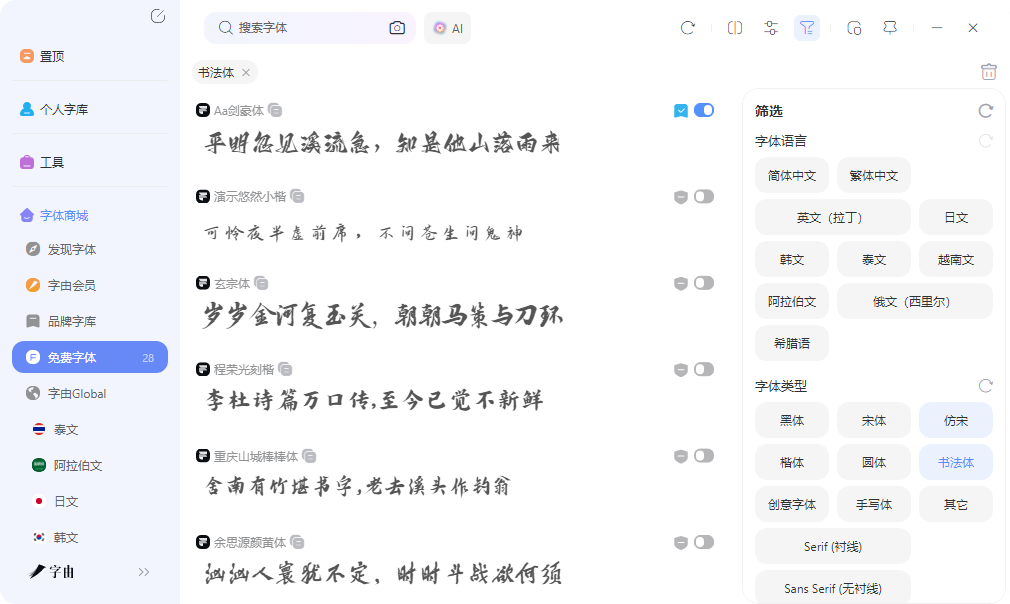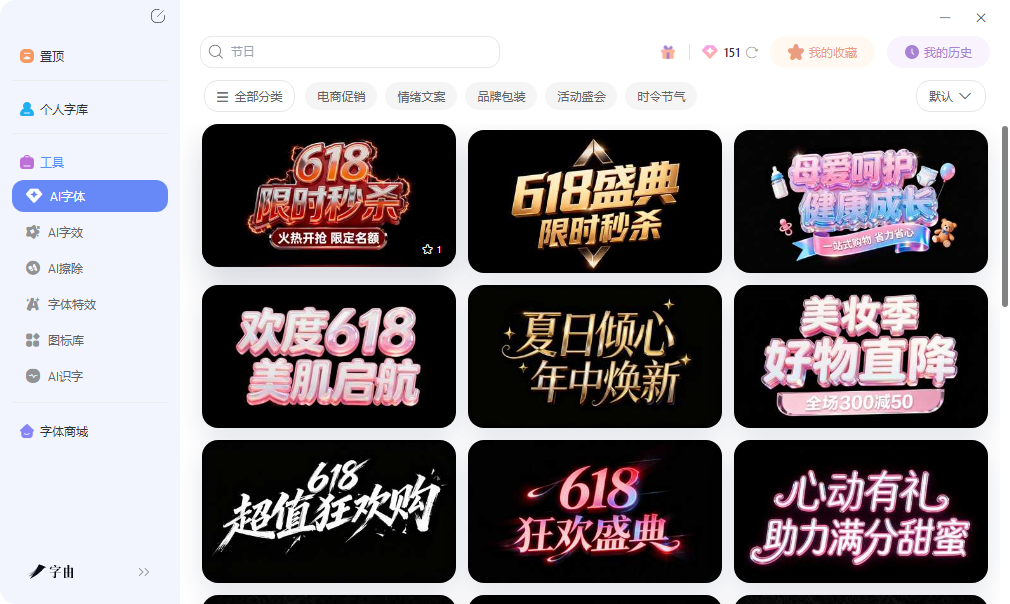
可以免费用的字体下载,中英文字体一站找齐
做设计最尴尬的事,不是创意卡壳,而是做到一半发现字体不能商用。很多人攒字体时只看效果不看授权,真到交稿时才发现某些字体仅限个人使用。与其事后补救,不如一开始就找可以免费用的字体渠道。这篇文章整理的五个平台,在商用授权方面都比较明确,中英文字体都有覆盖。
字由的字体库规模超过一万款,其中免费商用的超过三千款。这些字体来自优设、阿里妈妈、汉仪、蒙纳等正规厂商,授权链路清晰。每款字体的卡片上都标明了授权类型,免费商用、会员商用或单独授权一目了然。
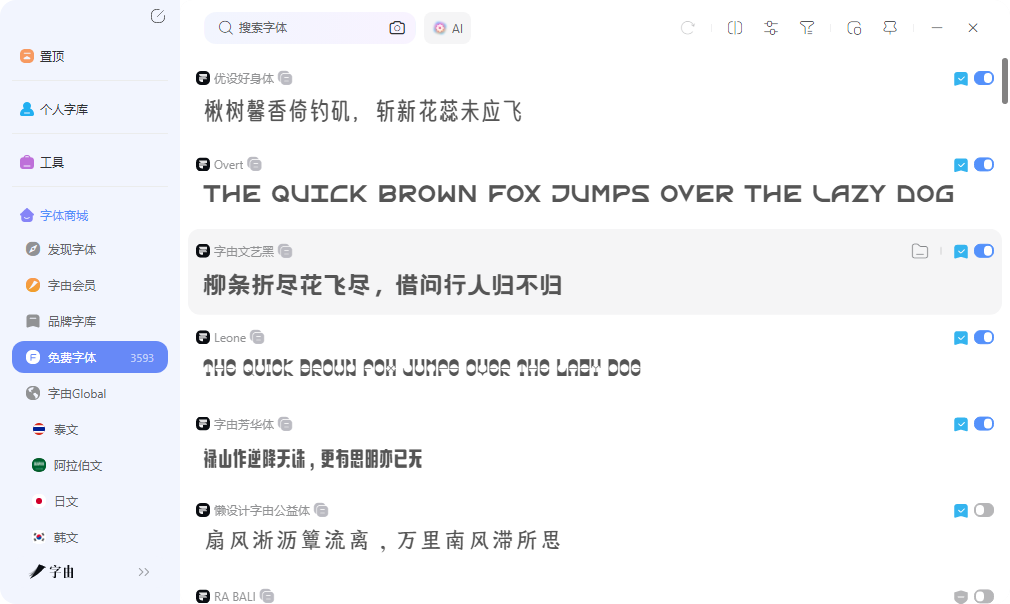
找书法体、手写体、黑体、宋体等不同书体时,左侧导航按类型分类,顶部还有风格和场景标签。做商务PPT就筛商务和现代,做文创项目就选手写和中国风,做科技类设计就点科技标签。这种多维度交叉筛选比按名称翻找要直观得多。
预览框支持输入自己的文案,调整字号和背景色,确认效果后再激活。激活后字体直接出现在Photoshop、Illustrator、Figma等设计软件中,不需要重启程序。取消激活也简单,点一下开关即可。字体文件不进入系统目录,换设备登录同一个账号就能恢复,不会在C盘堆积。
AI字体和AI字效是字由的两个辅助工具。AI字体偏向整体风格渲染,水墨、鎏金、霓虹等效果可以直接生成透明背景的PNG图片。AI字效偏向局部特效叠加,发光、投影、描边等可以精细调节。免费用户每日有算力额度,登录赠送的点数足够日常轻量使用。
2、Befonts
Befonts是一个免费字体收录平台,资源量比较大,覆盖的类型也比较全。从基础的无衬线体到装饰性强的展示字体,从手写体到书法体,几乎各种风格都能找到。平台上很多字体采用OFL开源协议,商用时比较放心。
分类体系做得比较细致,可以按风格标签逐步筛选。每款字体都配有展示图,部分还提供了多字重下载。Befonts的更新频率不错,经常能看到新上架的字体资源。对于喜欢大量浏览、慢慢淘字体的用户来说,这里的资源量和分类精细度都比较够用。
Befonts作为可以免费用的字体来源,其优势在于资源量大、覆盖风格广,适合需要储备多种类型字体的设计师。下载前建议仔细看一下授权说明,确认商用条款后再使用。
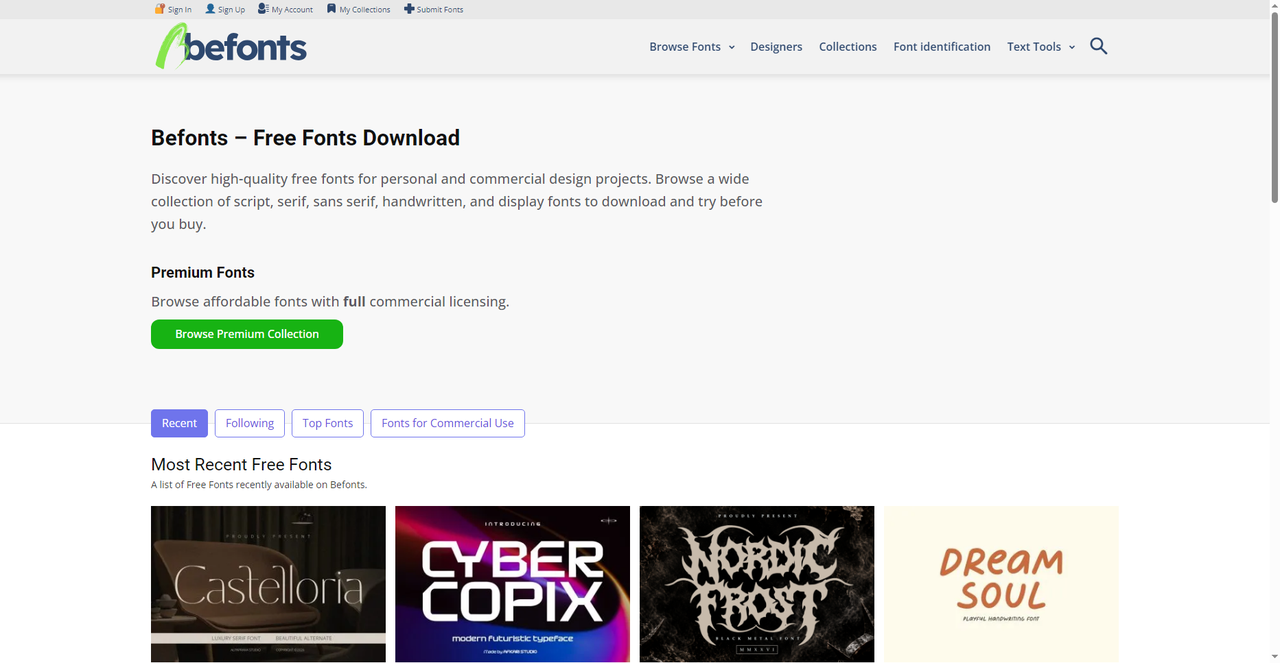
3、Velvetyne Type Foundry
Velvetyne是一个法国独立字体厂牌,专注于开源创意字体。和前面几个平台不同,Velvetyne不是字体聚合站,而是字体设计和发行机构,平台上的字体全部由团队自己设计或与合作设计师共同开发。
字体风格偏向实验性和艺术化,很多设计带有独特的视觉个性。比如Fusée是一款几何感强的无衬线体,Garoa则是带有巴西现代主义气质的字体。这些字体在常规渠道不太容易找到,适合追求差异化、不想用大众字体的设计项目。
所有字体都采用开源协议,允许商用和修改。Velvetyne在可以免费用的字体领域属于比较小众但品质很高的选择,适合对字体独特性有要求的项目。浏览体验简洁,每款字体都有详细的设计说明和字符集展示。
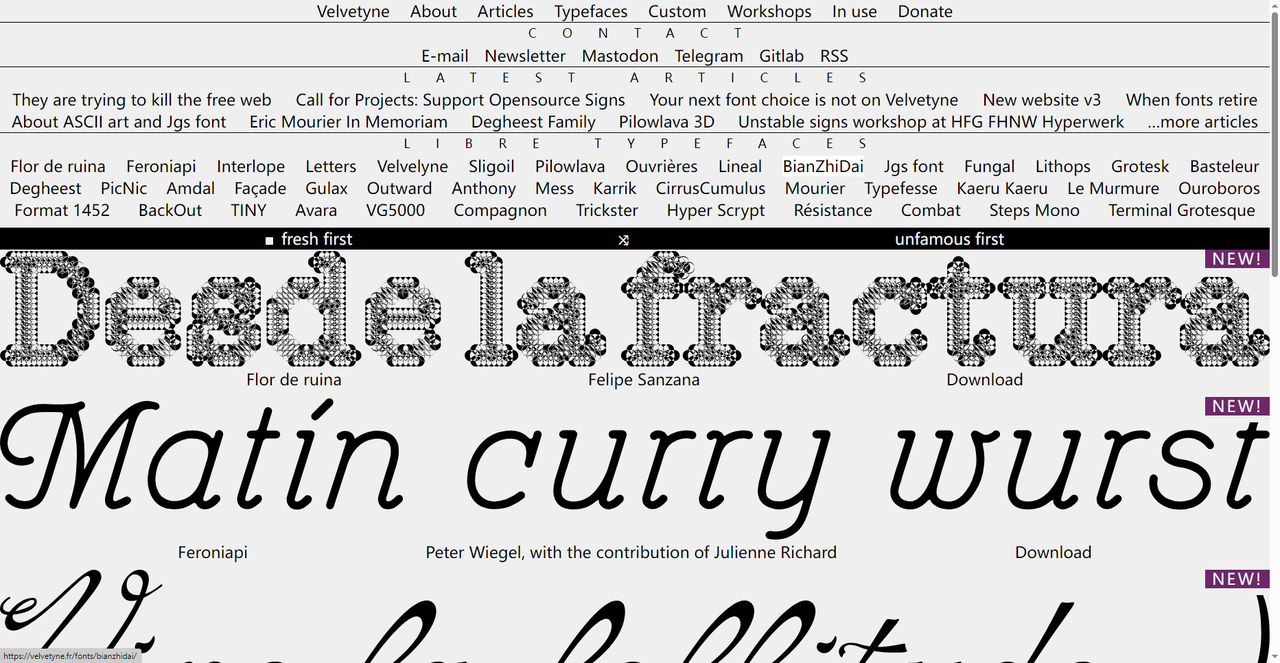
4、Font Squirrel
Font Squirrel是2009年创立的老牌免费字体平台,由设计师Derek Weathersbee发起。这个平台有一个比较严格的机制:只收录100%免费商用的字体,并且每款字体都经过手动授权验证。如果发现某款字体后期改变了授权政策,平台会立即下架。
目前收录的字体覆盖Sans Serif、Serif、Display、Handwritten、Script等多种类型。每款字体都有清晰的展示图和下载按钮,部分字体还提供Web Font Generator工具,可以把字体文件转换为网页可用的格式。对于需要在网站中嵌入字体的开发者来说,这个工具比较实用。
Font Squirrel的筛选体系支持按风格、热度、最新上架等维度排序,找字效率较高。平台上还提供了字体识别工具Matcherator,上传图片可以识别字体名称。作为可以免费用的字体渠道,Font Squirrel在授权严谨性和工具丰富度方面有比较突出的优势。
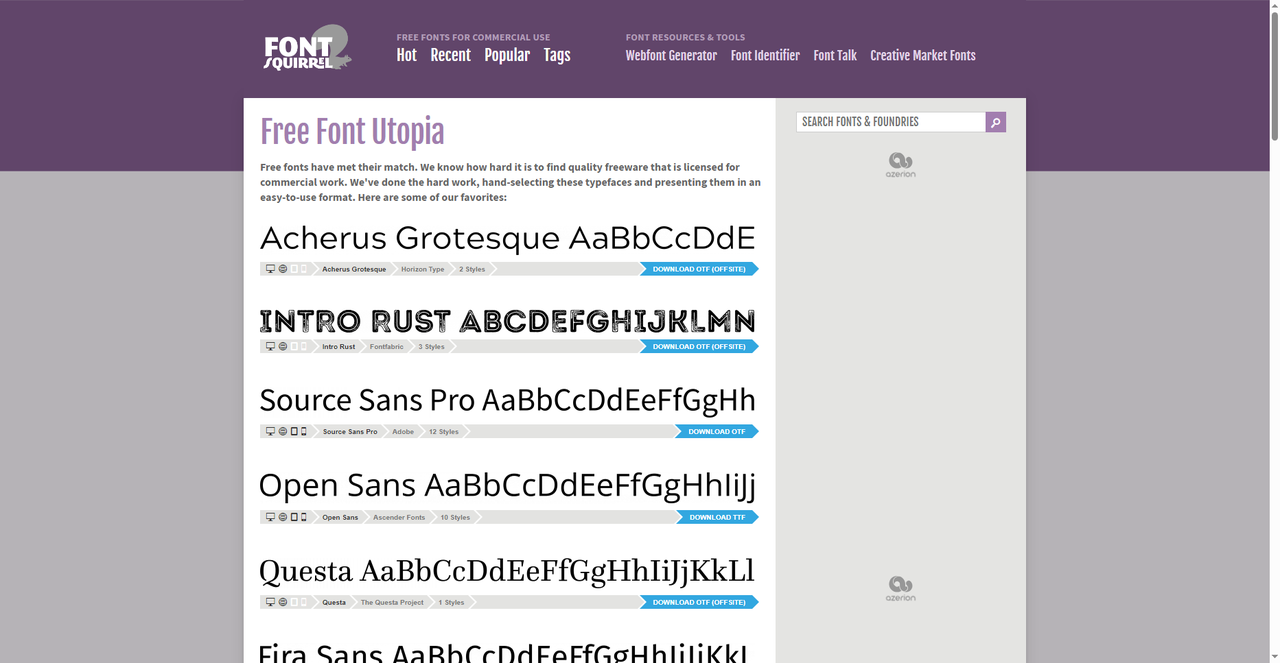
5、Fontshare
Fontshare由印度字体工厂Indian Type Foundry运营,2021年上线,平台上的所有字体全部免费商用。这个平台的特点是选品偏向现代设计感,收录的字体在网页设计、品牌视觉和时尚类项目中表现不错。
知名字体包括Clash Display(几何感强的展示字体)、Cabinet Grotesk(简洁现代的无衬线体)、Satoshi(中性气质的人文主义无衬线体)、Panchang(阿拉伯风格装饰体)等。每款字体都提供多个字重和变体,做完整的排版系统时比较实用。
浏览方式比较灵活。首页有风格标签可以筛选,比如Display、Sans Serif、Serif、Mono等大类,还有Variable Fonts选项可以筛选可变字体。预览框支持输入自己的文案查看效果,下载按钮直接获取字体文件。Fontshare作为可以免费用的字体来源,其选品质量在免费字体平台中属于较高水准,适合对设计感有要求的项目。
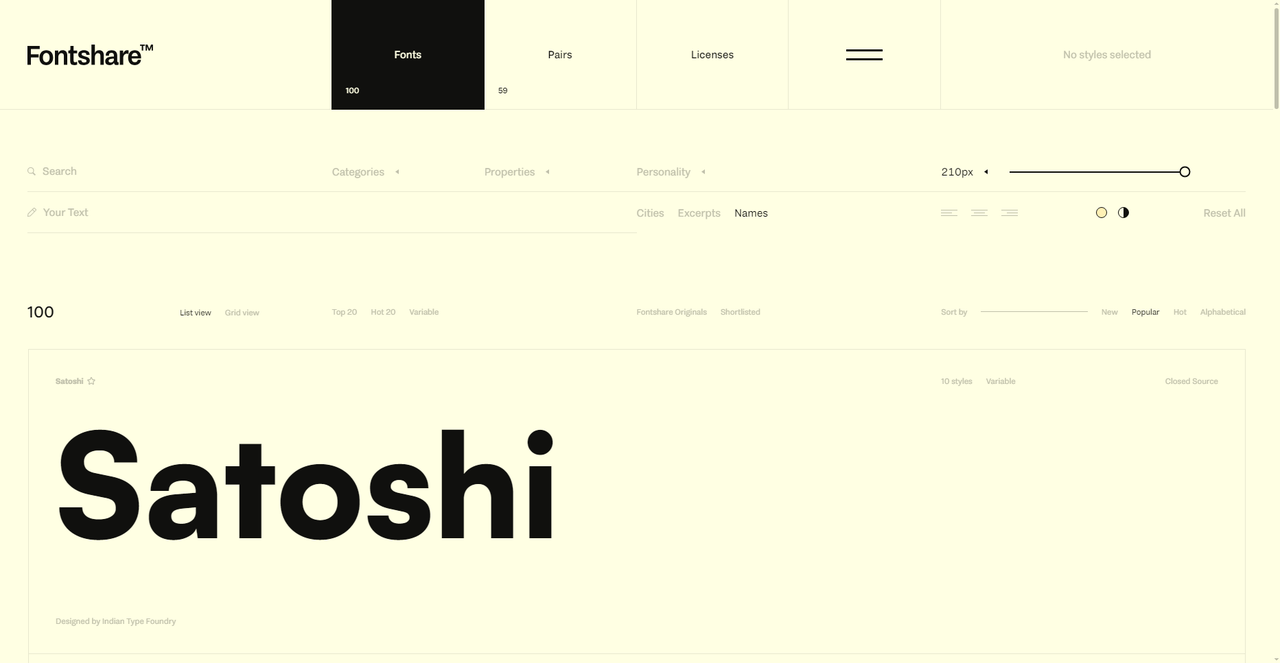
做中文商业项目,字由的免费商用筛选和一键激活在效率和便捷性方面表现突出,三千多款可以免费用的字体覆盖主流需求。Fontshare的现代设计感字体适合网页和品牌项目。Font Squirrel授权严谨、工具丰富,是值得信赖的老牌渠道。Befonts资源量大、风格覆盖广,适合批量储备。Velvetyne则提供了常规渠道找不到的独特创意字体。五个平台各有侧重,按项目的语言需求和风格方向来选就行。